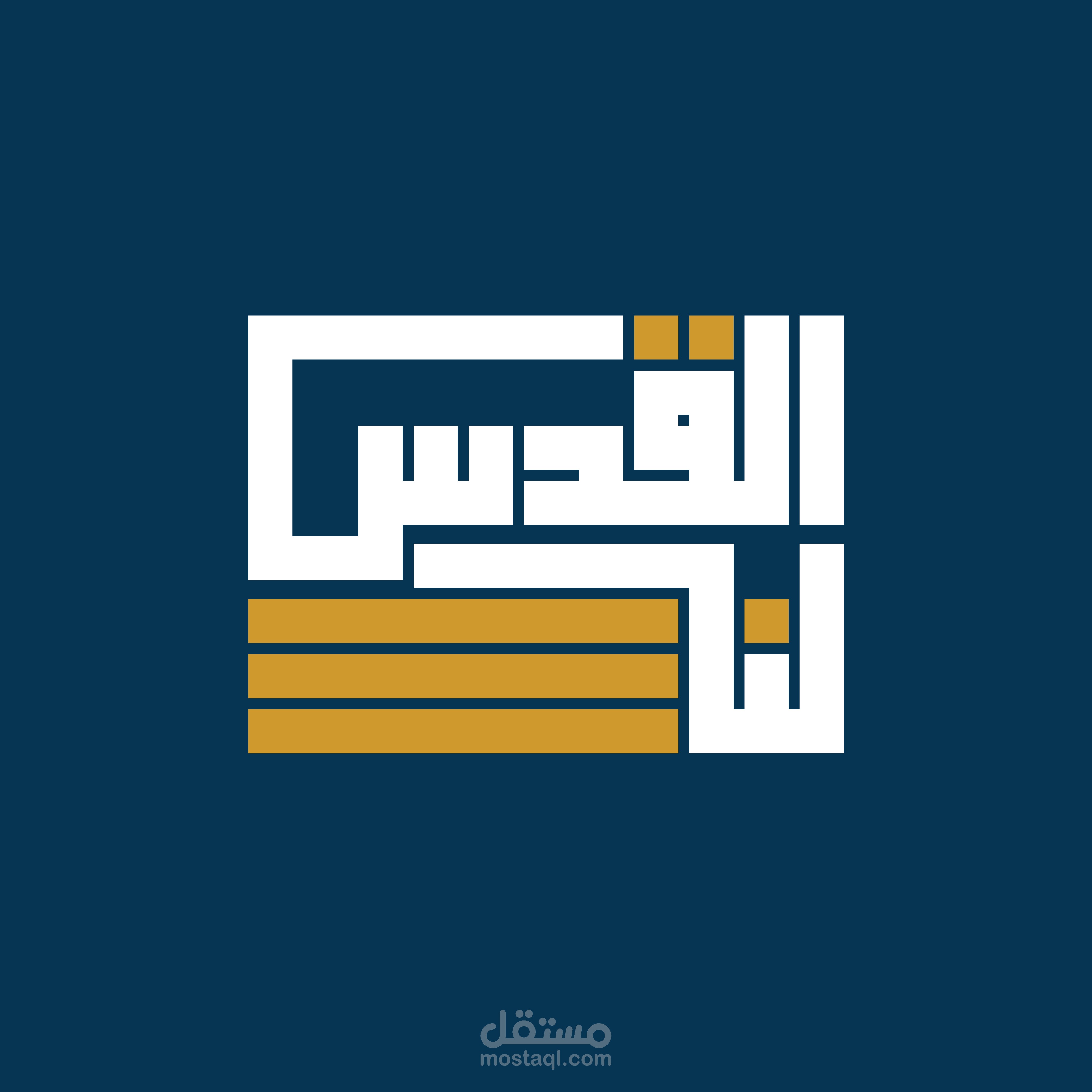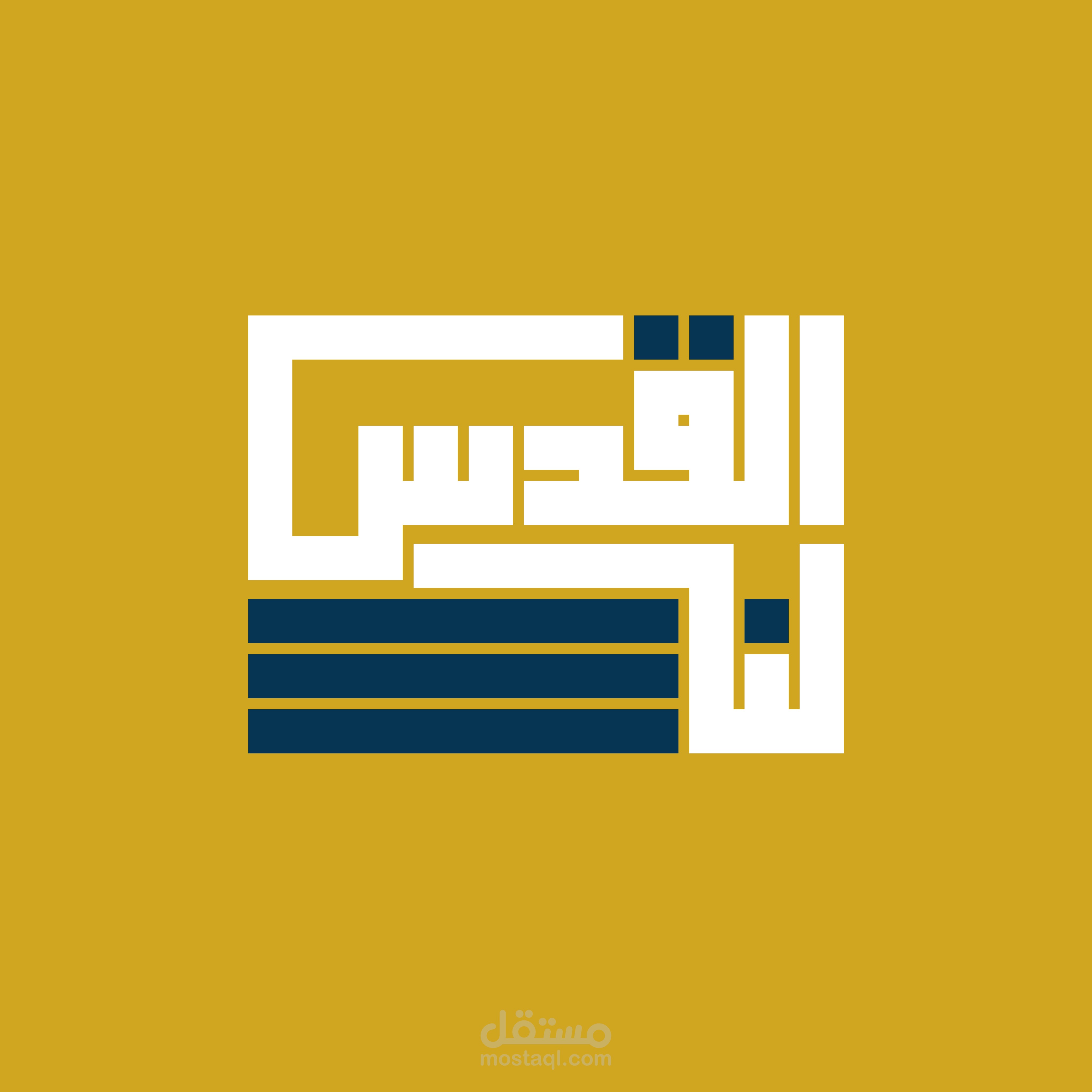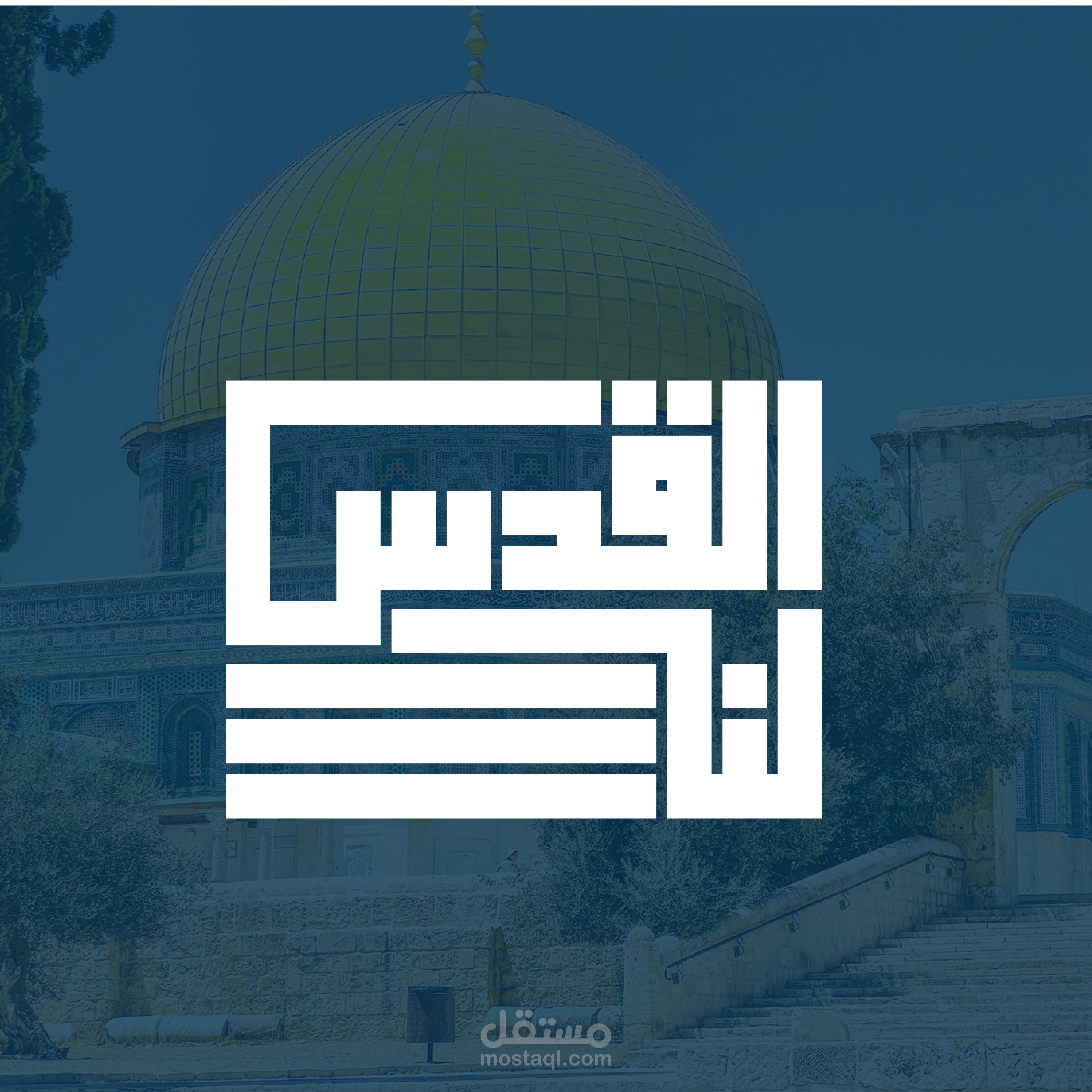
الخط الكوفي هو أحد أنماط الخط العربي التقليدي وهو واحد من أقدم الأنماط الخطية المستخدمة في الكتابة العربية. يعود أصل الخط الكوفي إلى مدينة الكوفة في العراق، وقد تطور في القرن الأول الهجري.
يتميز الخط الكوفي بطابعه الجميل والديكوري، حيث يتميز بالأشكال الهندسية المعقدة والزخارف الجميلة. يعتمد الخط الكوفي على استخدام الخطوط العريضة والمستقيمة والزوايا الحادة، ويتم تنسيق الحروف والكلمات بشكل متراص ومتناسق.
الخط الكوفي استخدم في الأساس في كتابة المصاحف والمخطوطات الدينية، وتجده أيضًا في العمارة الإسلامية في الزخارف والنقوش على الجدران والأعمدة.
تعد أشكال الخط الكوفي المعروفة هي الكوفي المعتاد والكوفي الرقعة والكوفي المربع والكوفي المعنقد والكوفي المفرغ. تختلف هذه الأشكال في تصميم الحروف وترتيبها، ولكل منها طابع فني وجمالي خاص.